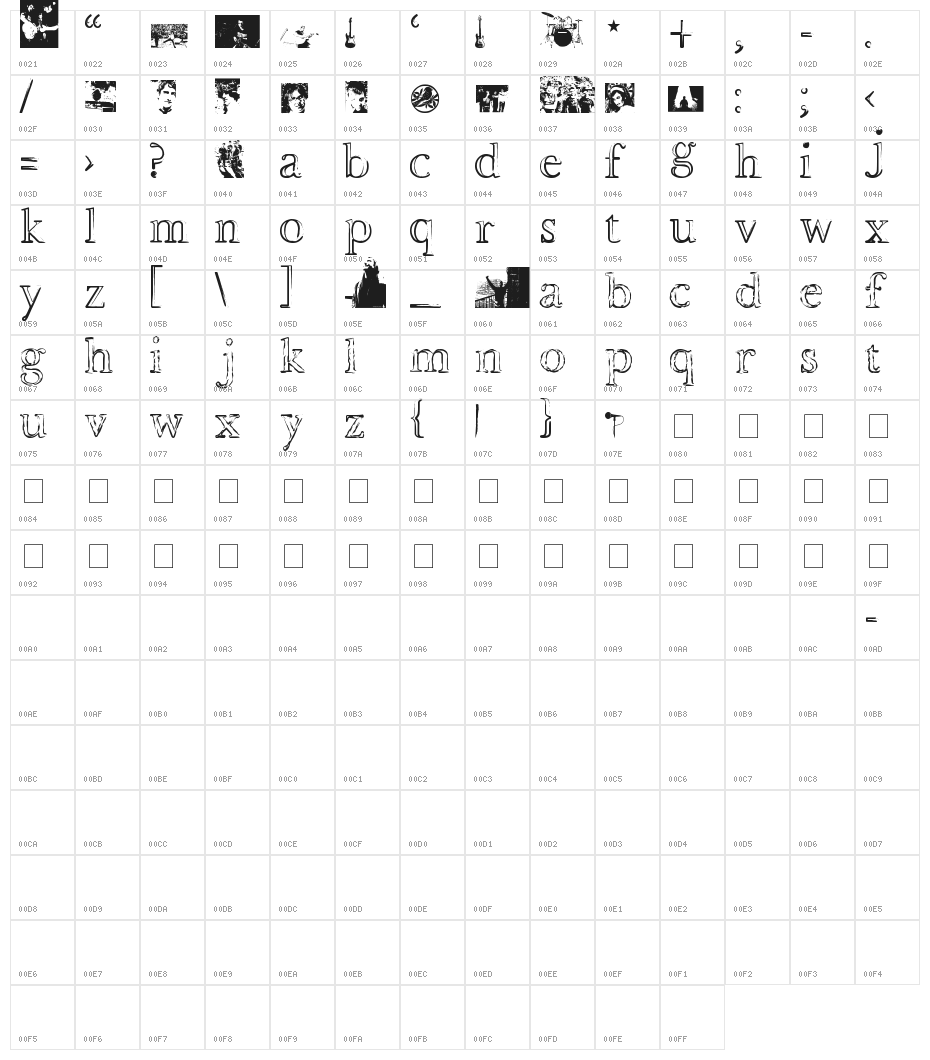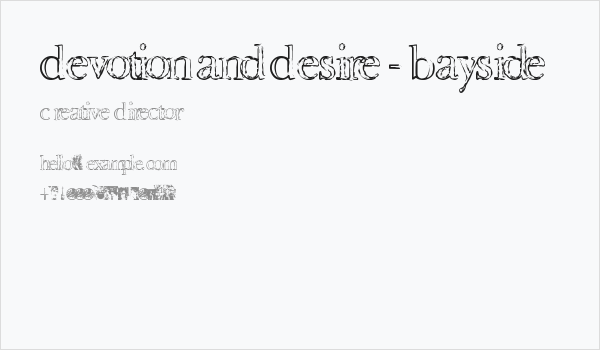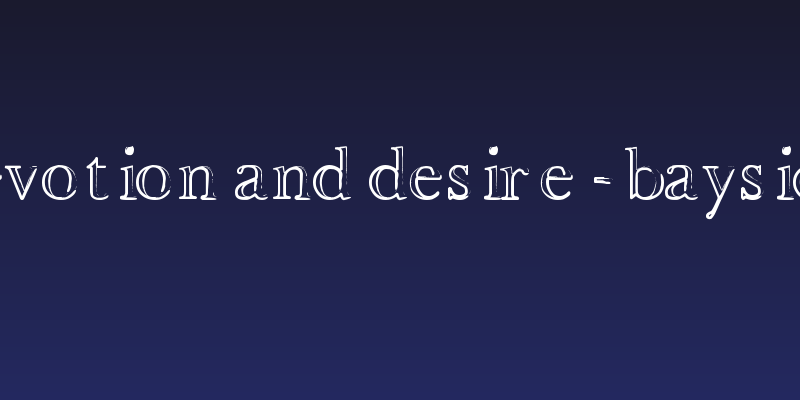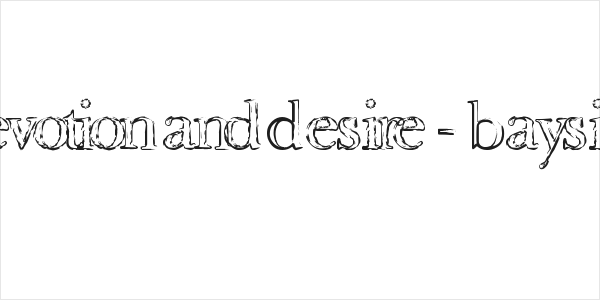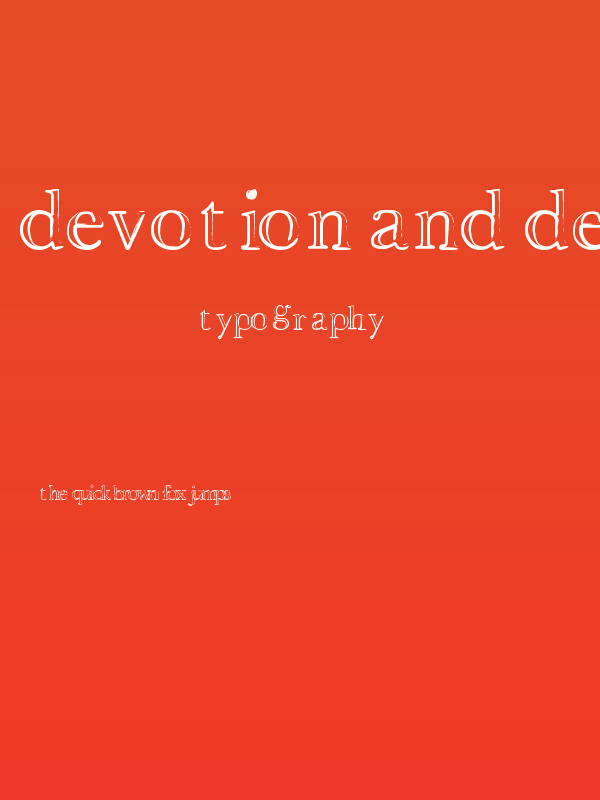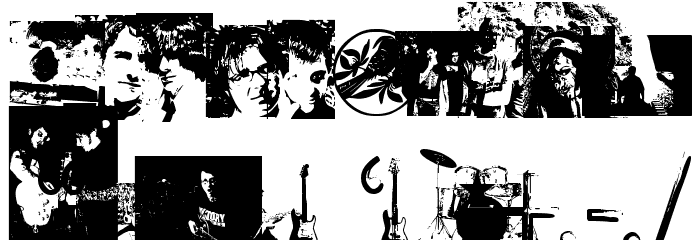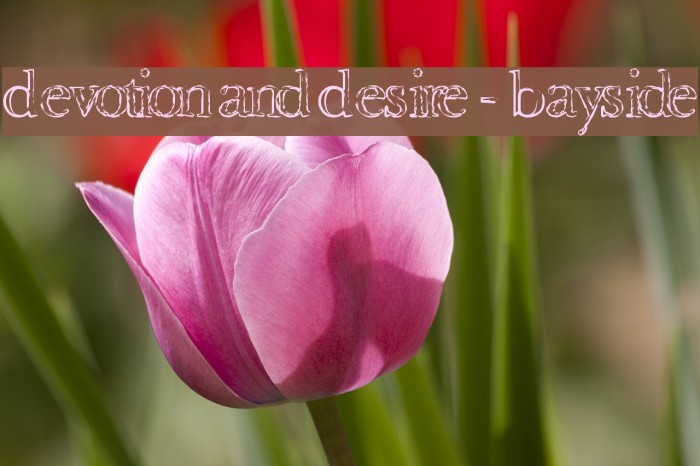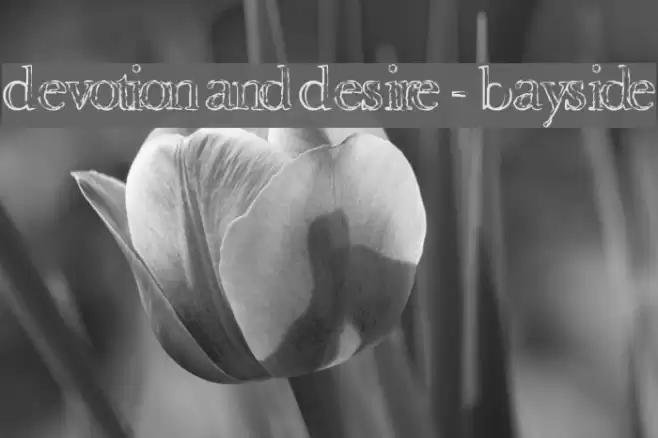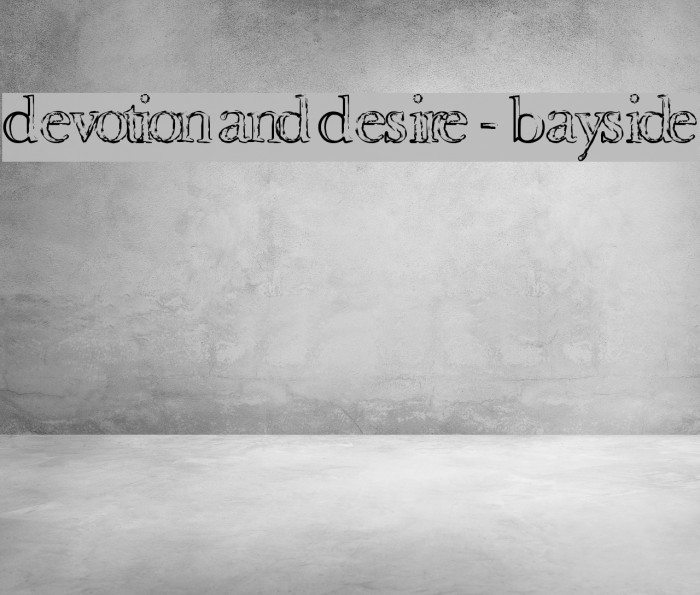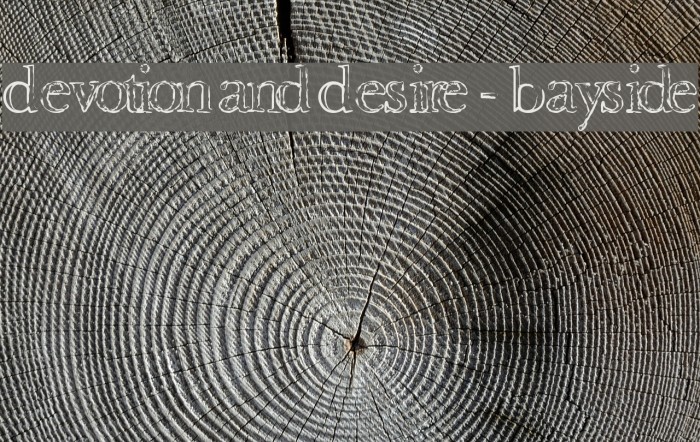
Devotion and Desire - Bayside Font
✎ Messy
| Anwendungsfall | Logos, Headlines, Posters |
| Vorgeschlagene Projekte | Ideal for album covers, posters, and designs that require a bold, artistic statement. |